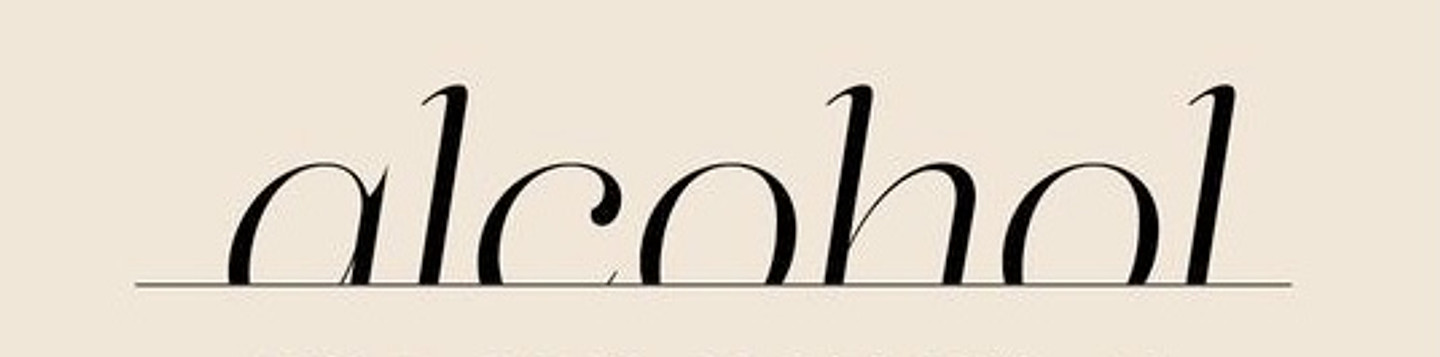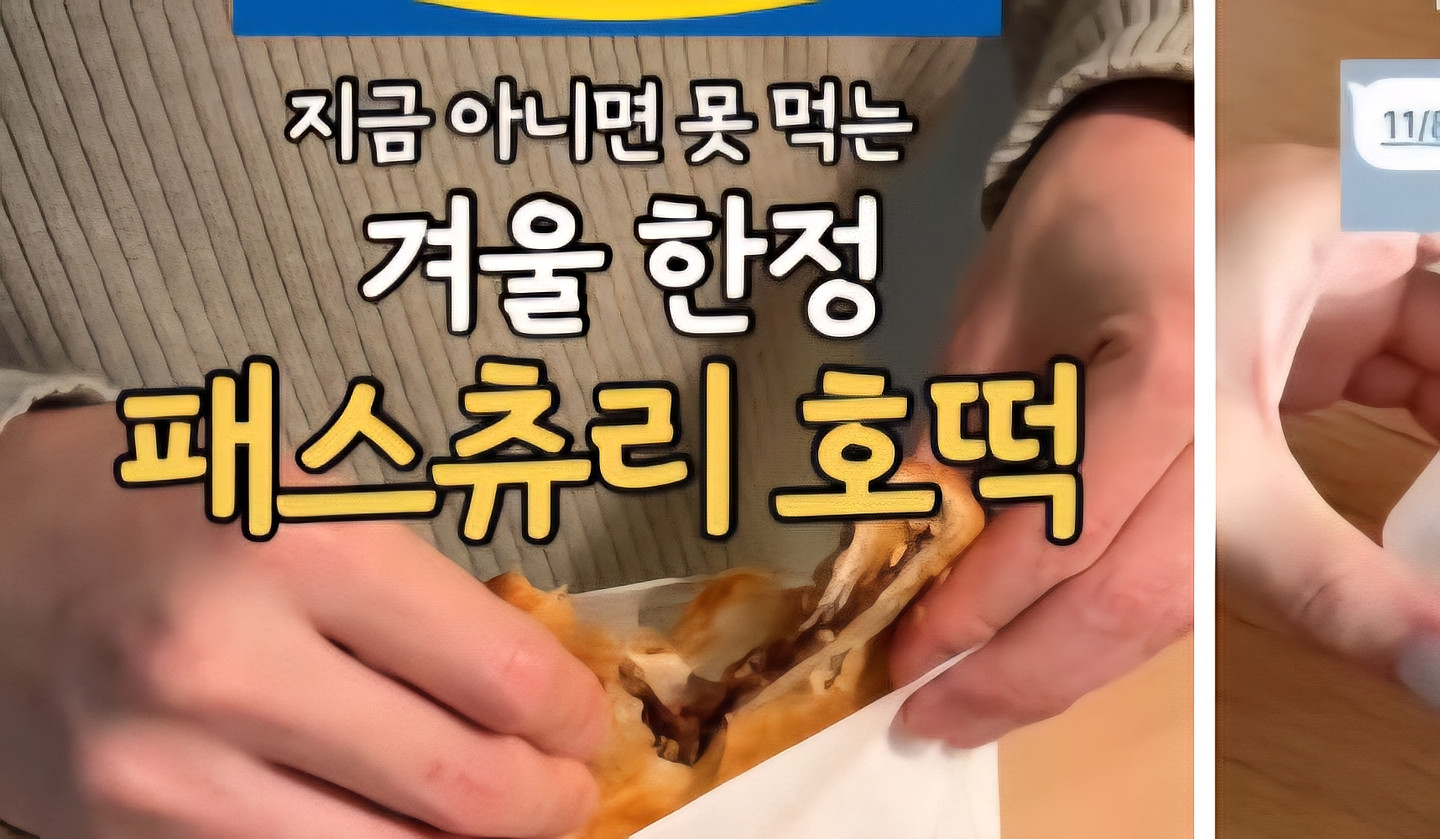
안녕하세요 핀터레스트에서 본 건데 혹시 어떤 폰트인지 아시는 분 계실까요? 정말정말 알고 싶어서 찾고 있는데 어렵네용ㅠㅠㅠ
이 폰트 몬가요???? 앞 게시물 폰트랑 같은 건가요??????
이 폰트 몰까요?????? ㅠㅠㅠ
이거 폰트 ㄷ도대체 뭔가요 ㅠㅠ
주키니) < 이폰트랑 댓글 달러 < 이 폰트 둘다 궁금해요
무슨 폰트인지 궁금해요 ㅠ.ㅠ
뭔 폰트인가요...
이 폰트 뭘까요? 아시는분 ♥
이 폰트 뭘까요?ㅠ.ㅠ
명조 베이스인데 이미지 검색해도 안나오네요ㅠ 알려주시면 감사하겠습니다
흰색 글자 무슨 폰트일까요? ai도 못찾네요 ㅠ
무슨폰트일까요?-?
이 폰트가 뭔가요
어떤 폰트 일까요ㅜㅜ?